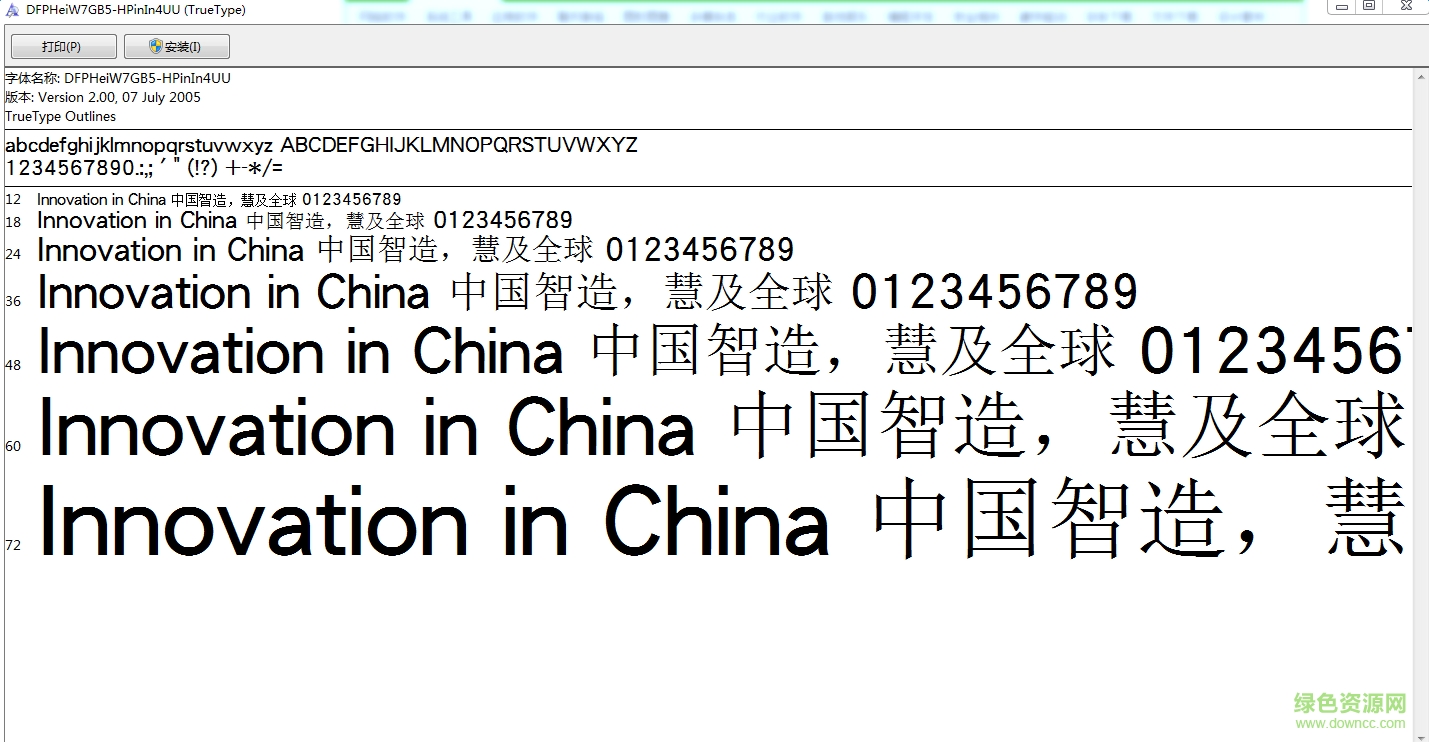
華康黑體W7漢音上U字體是一款華康類w7漢音黑體字體軟件,黑色的字體給人非常正規(guī)的感覺,深受廣大年輕人的喜愛,還有更多好看字體盡情期待,歡迎到綠色資源網(wǎng)下載體驗(yàn)!
華康黑體W7漢音上U是一款華康類w7漢音的黑體字,字體效果比較黑,喜歡黑體字的朋友可以下載使用看看效果如何。